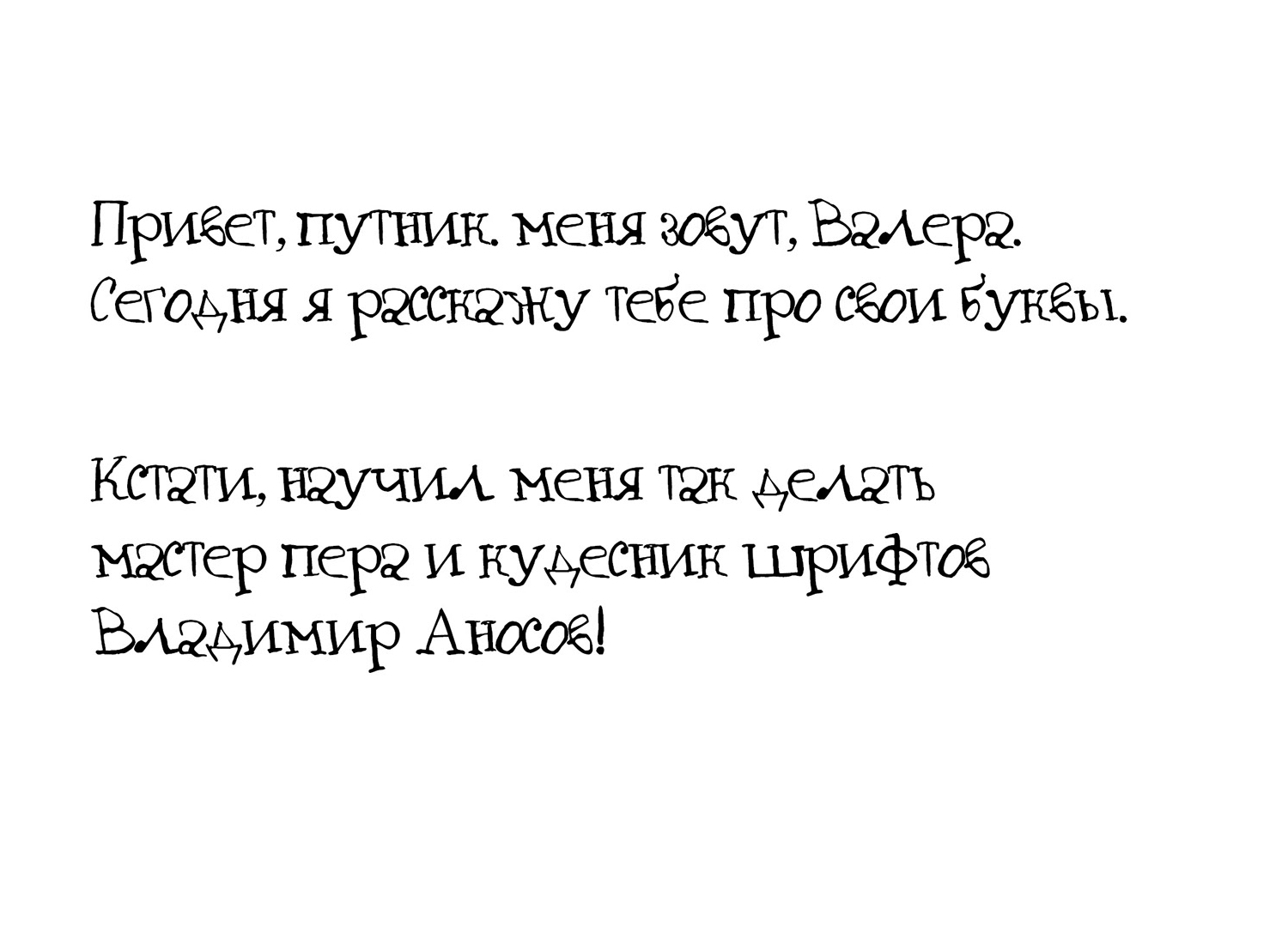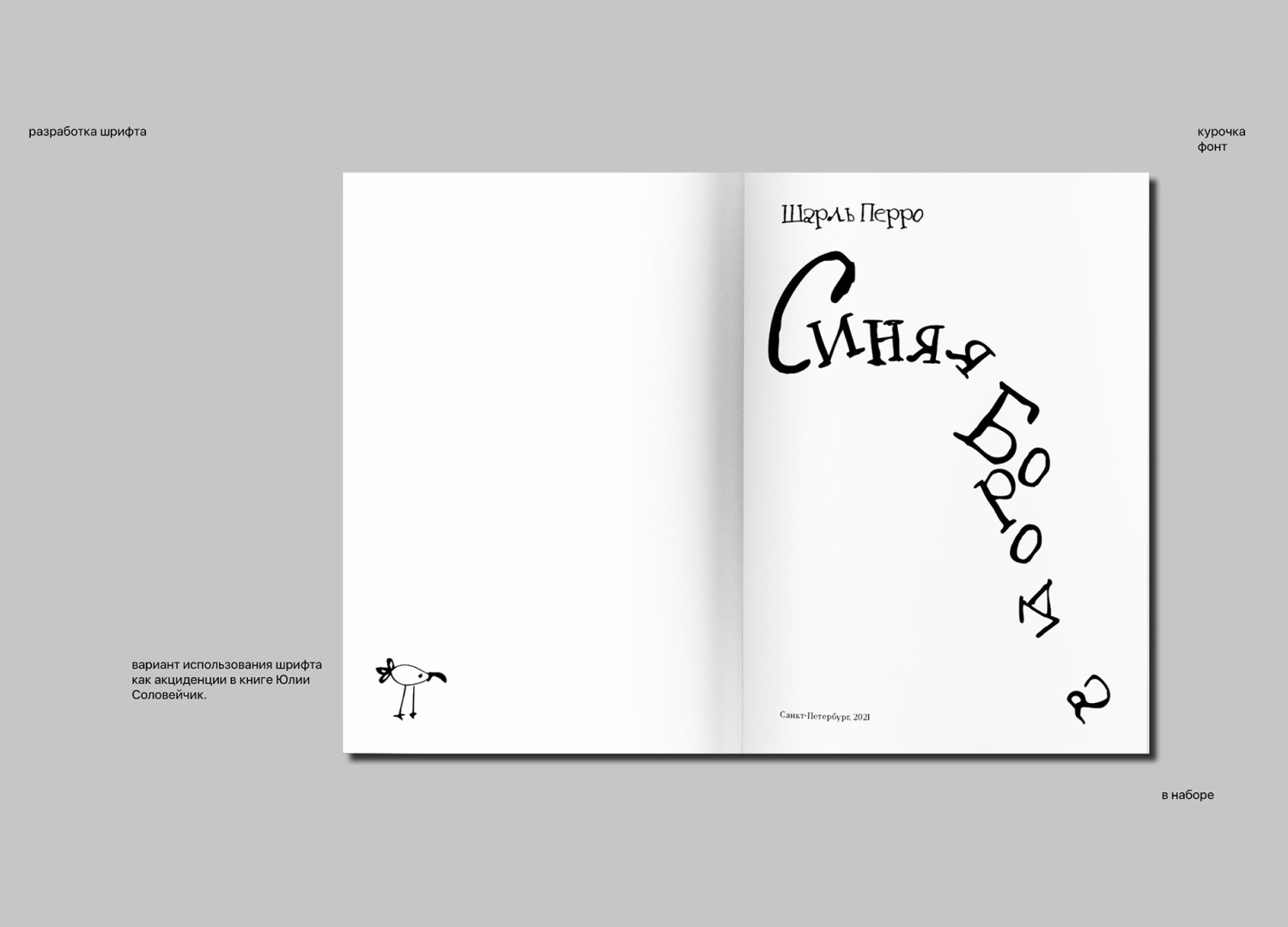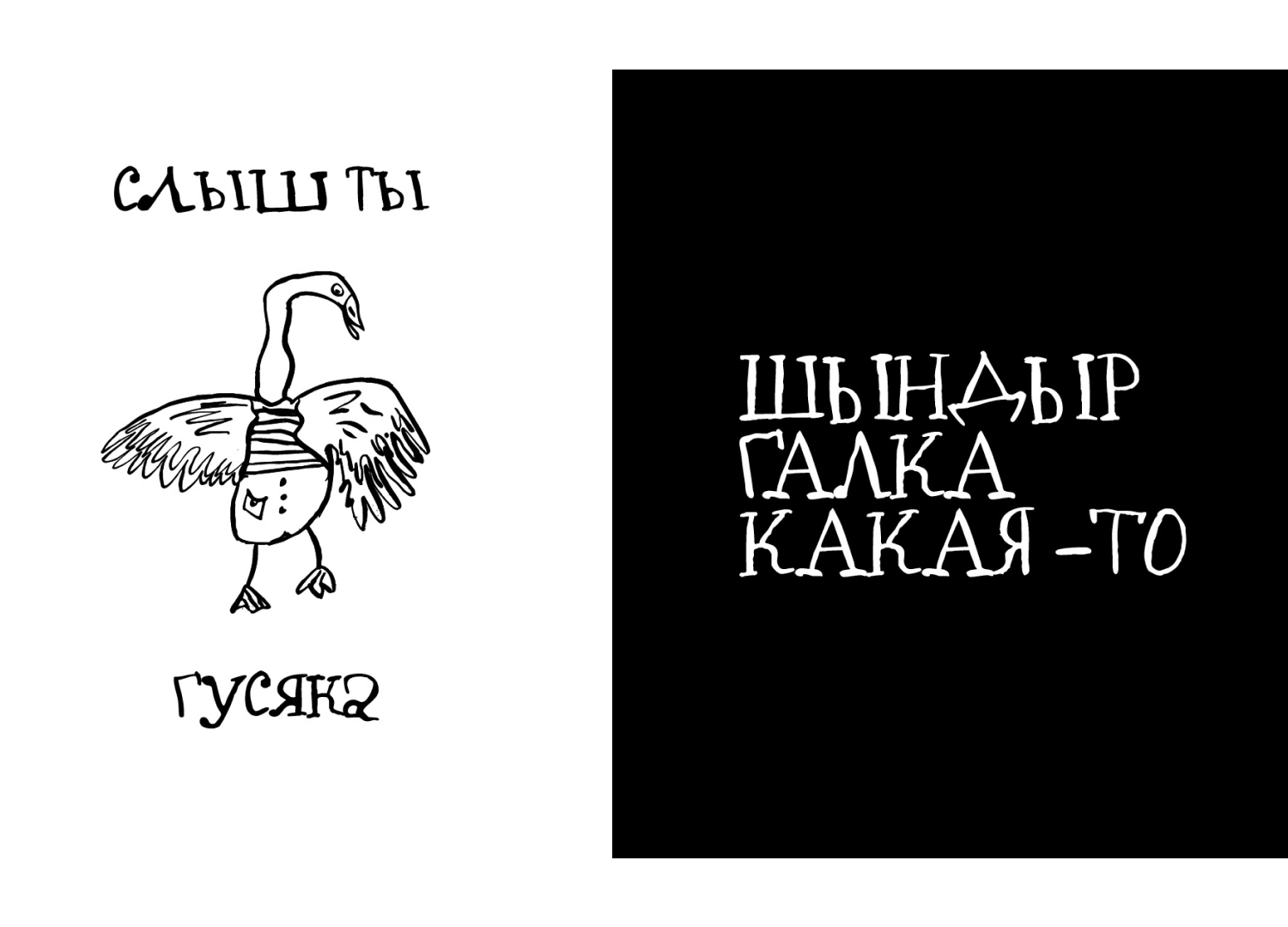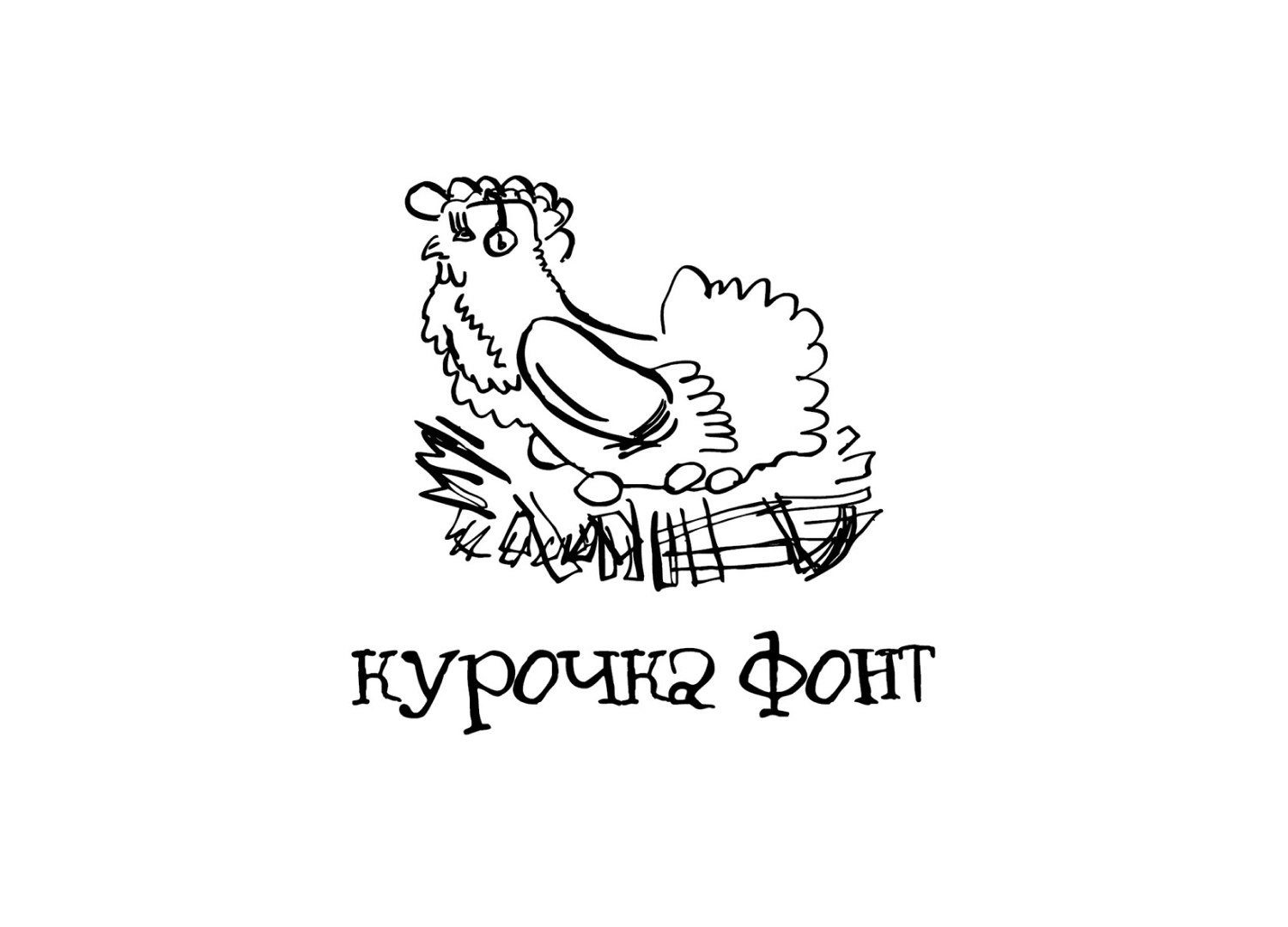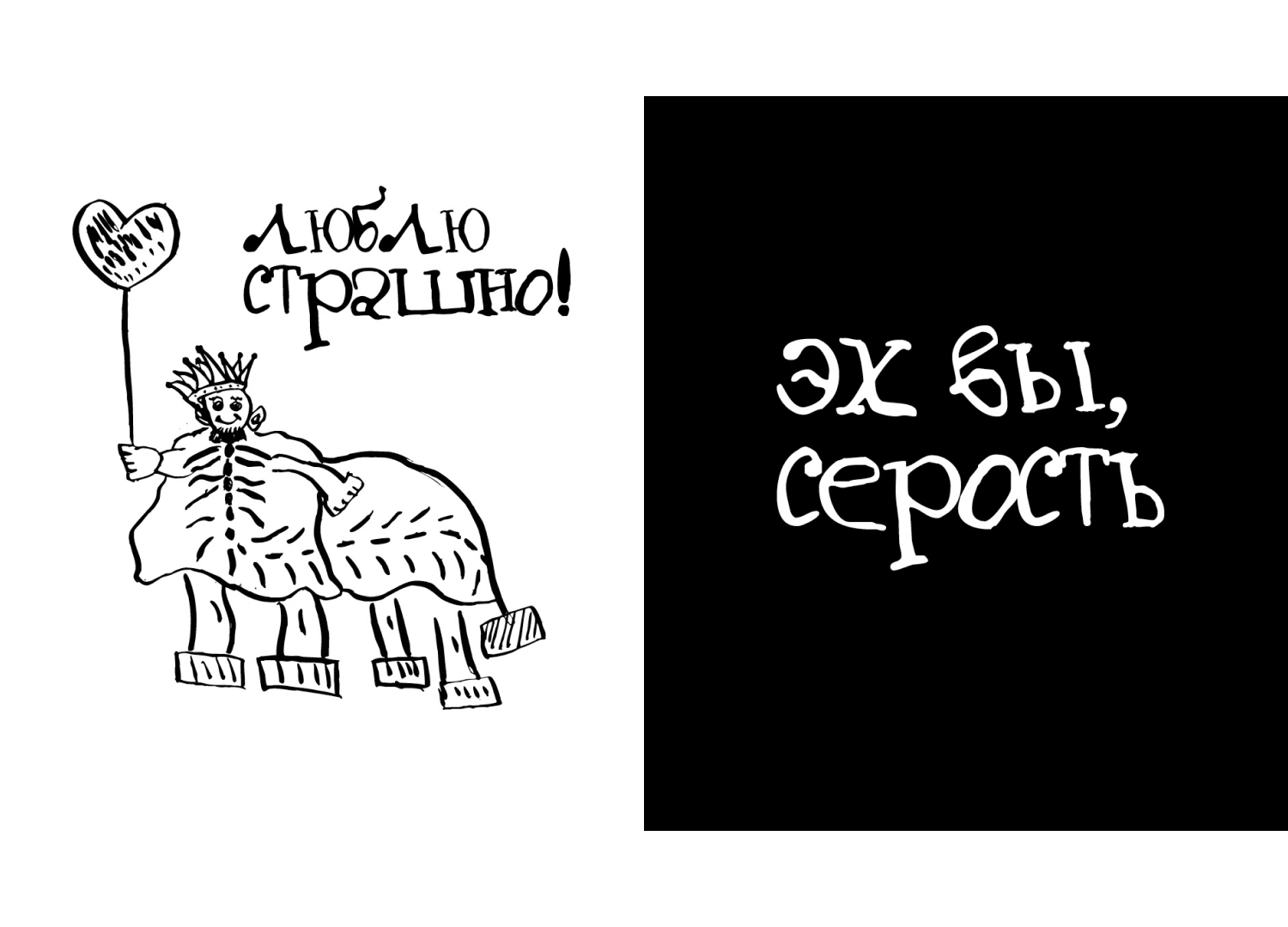
Шрифт курочка
Курочка) По названию понятно, что это будет слегка корявый шрифт) Но все равно лучше чем у многих из вас почерк) Автор: Valera Cherevkov. Бесплатно дл личного и коммерческого использования.